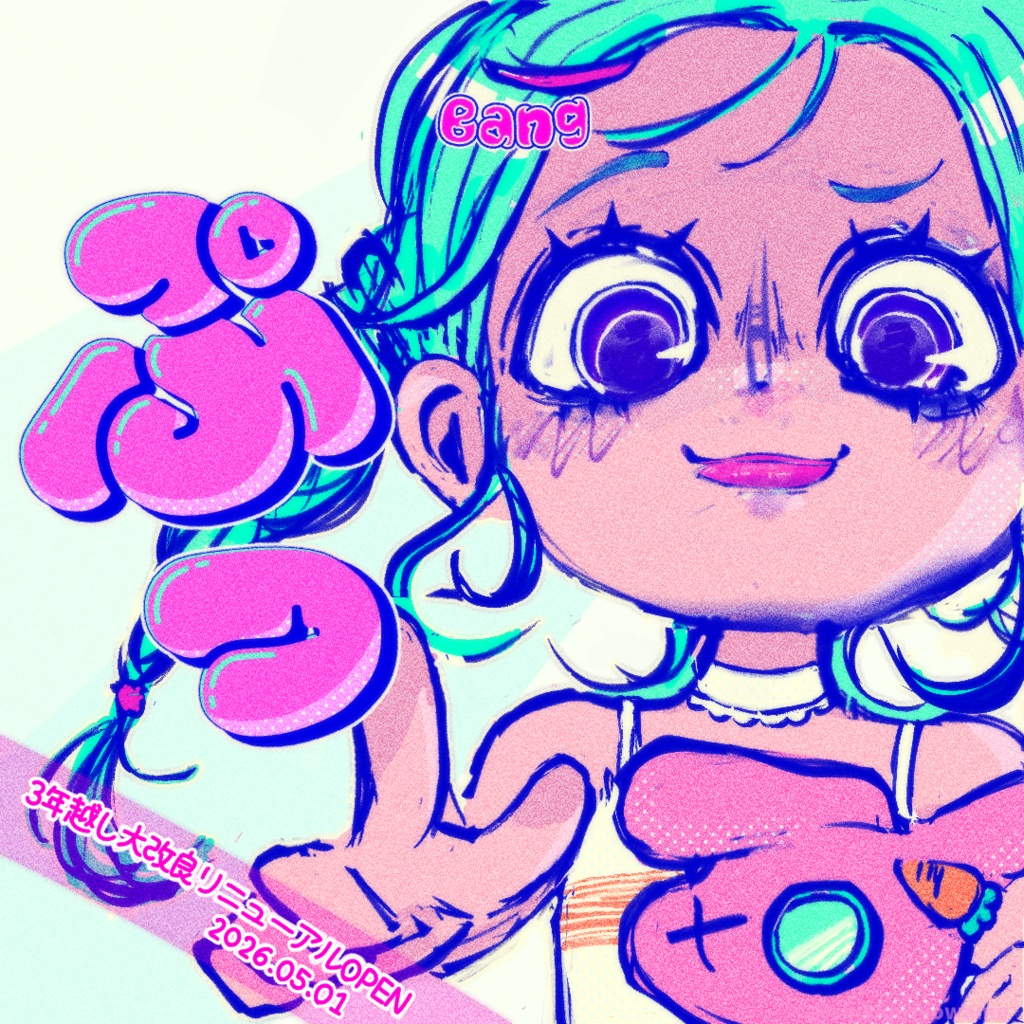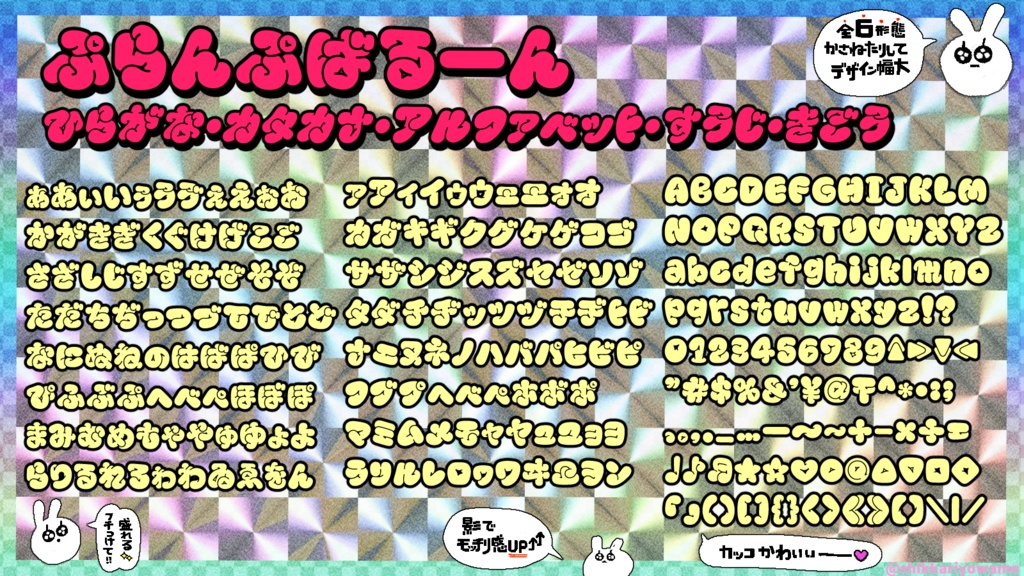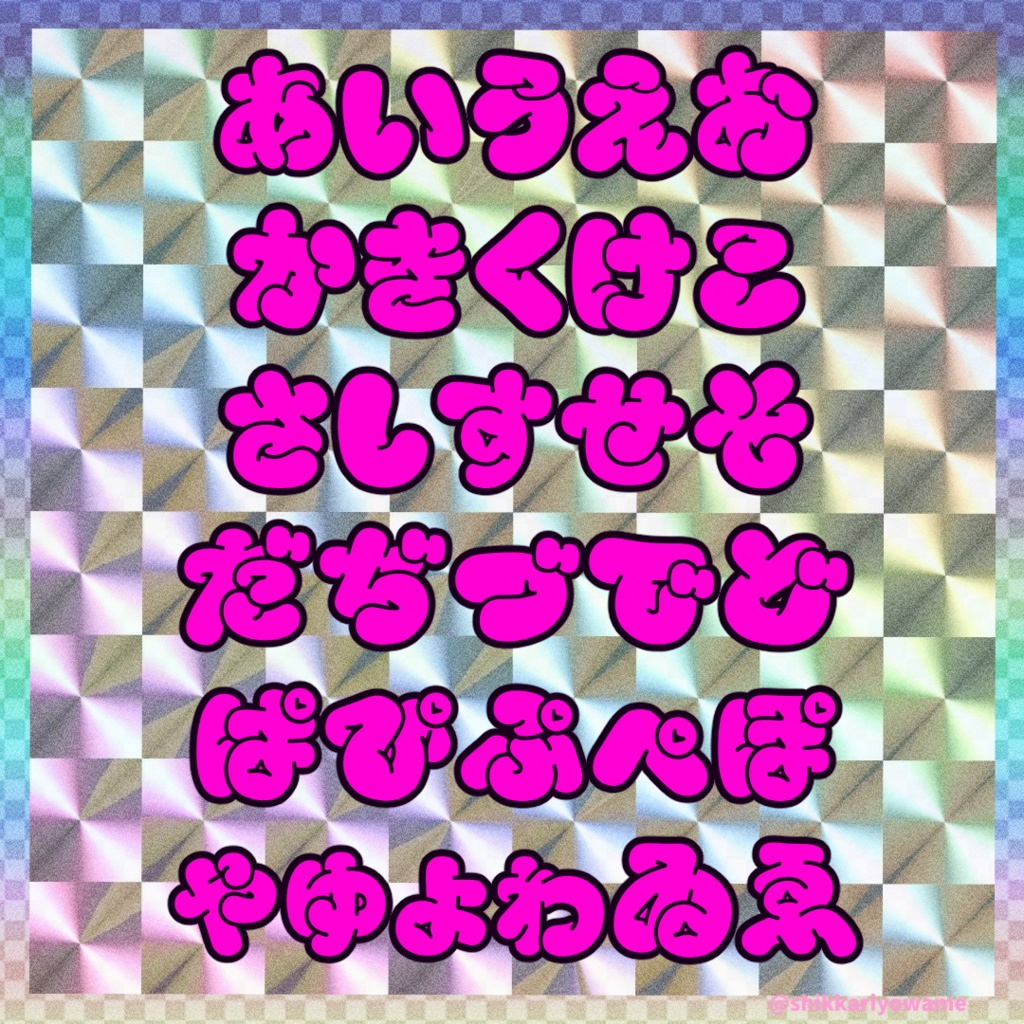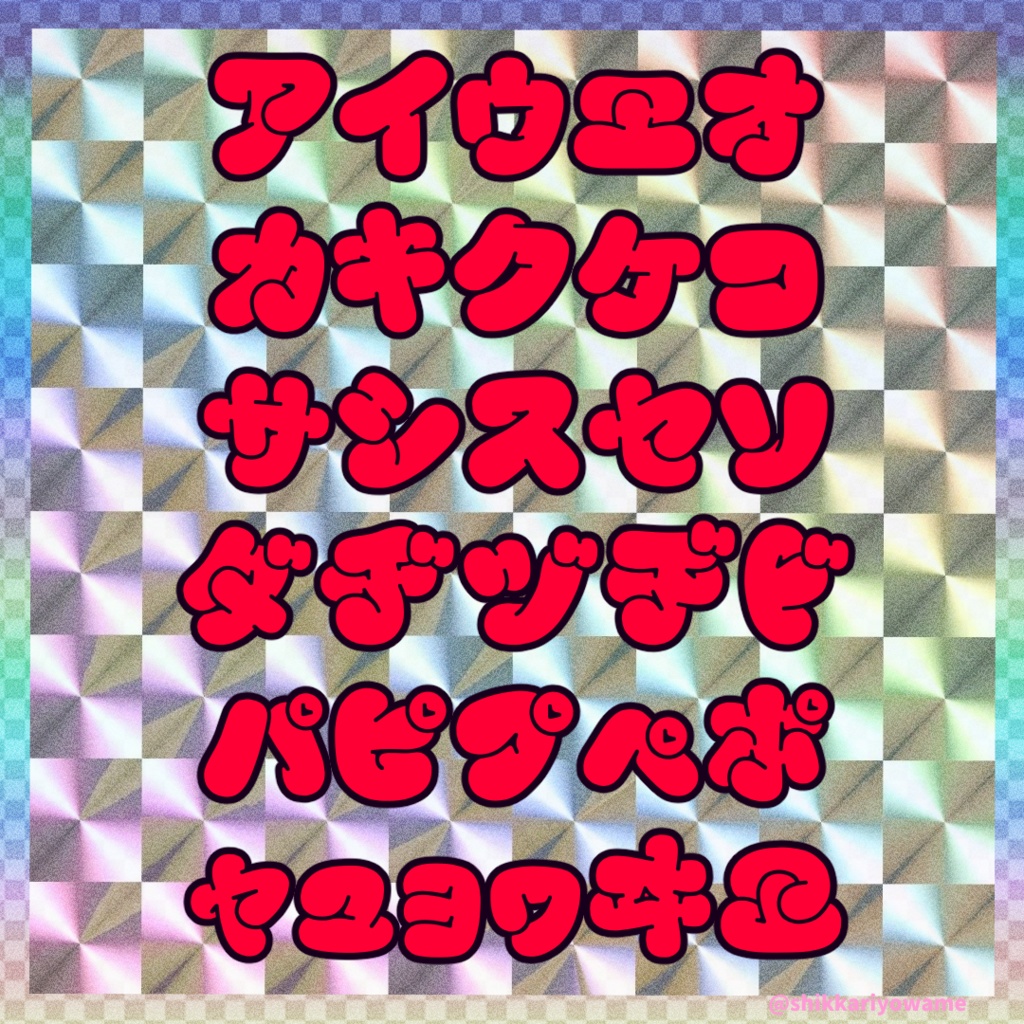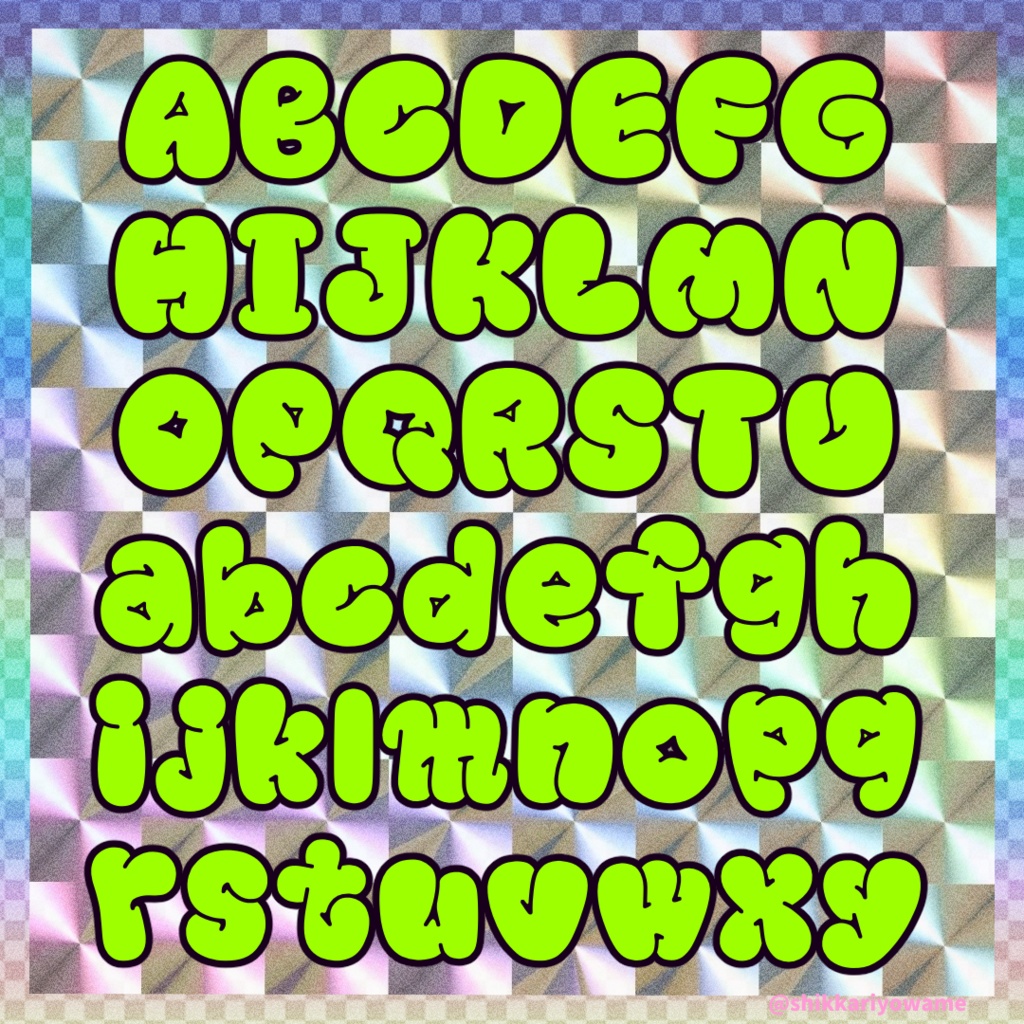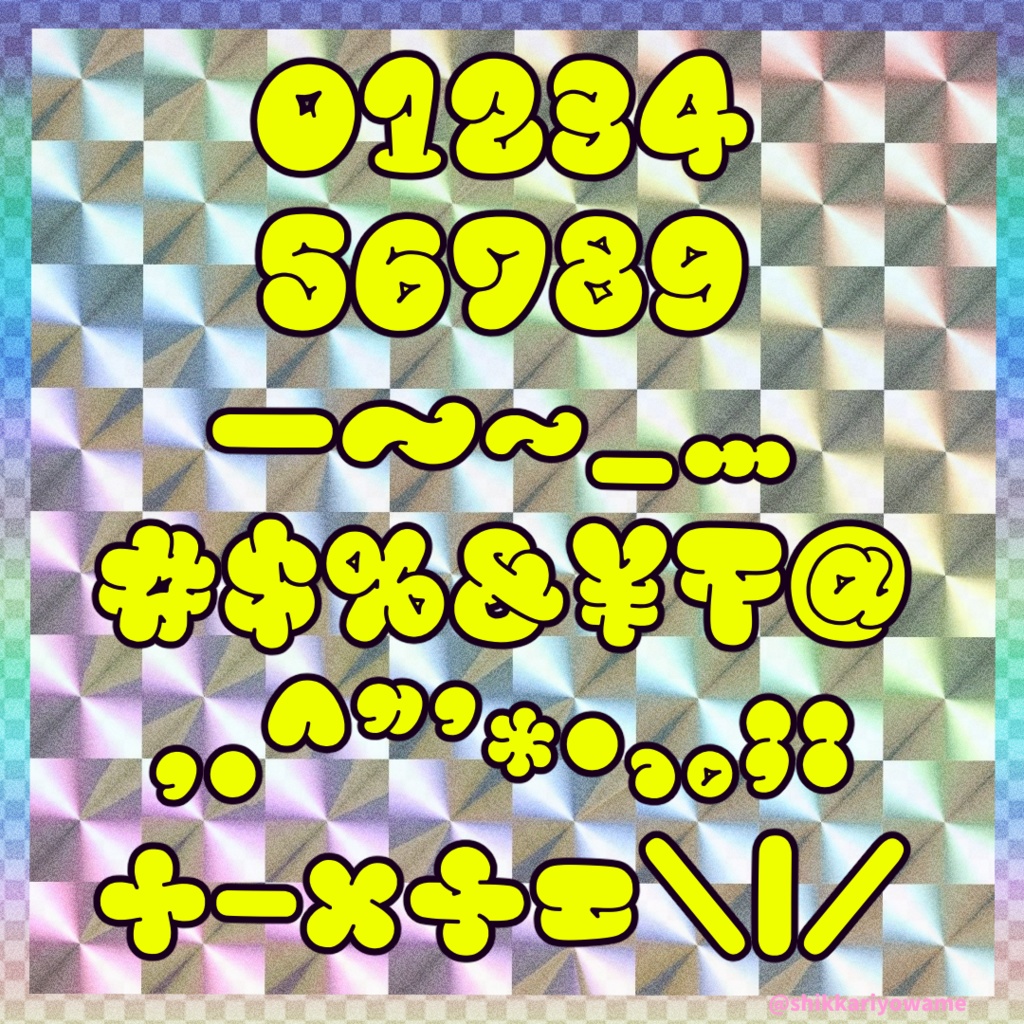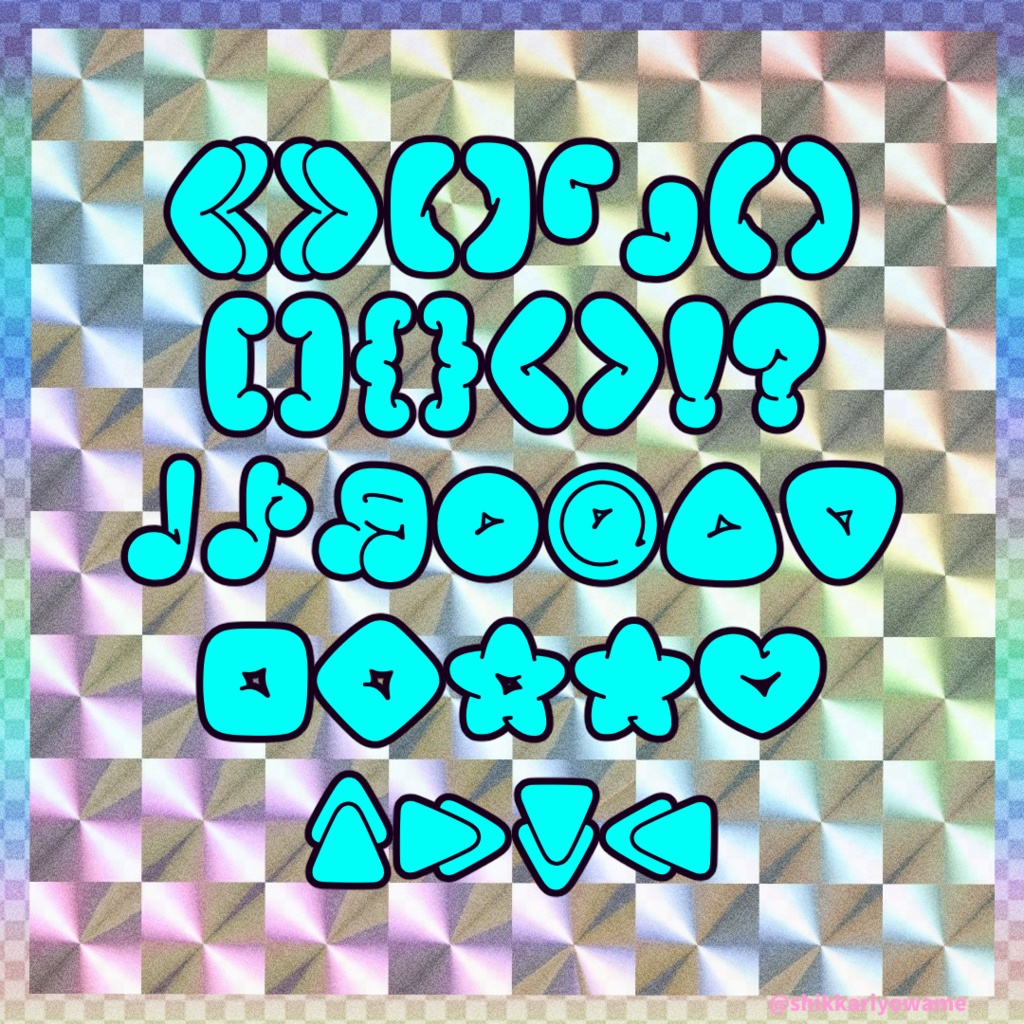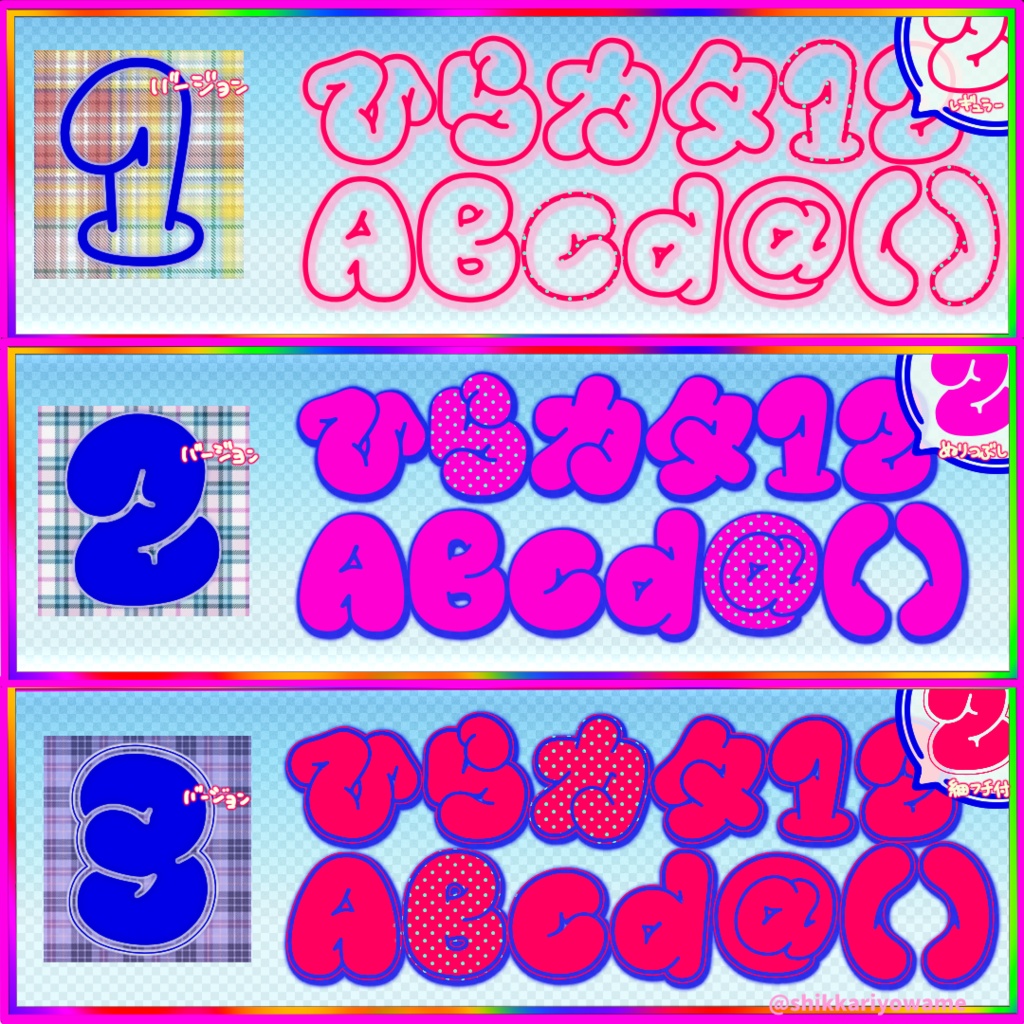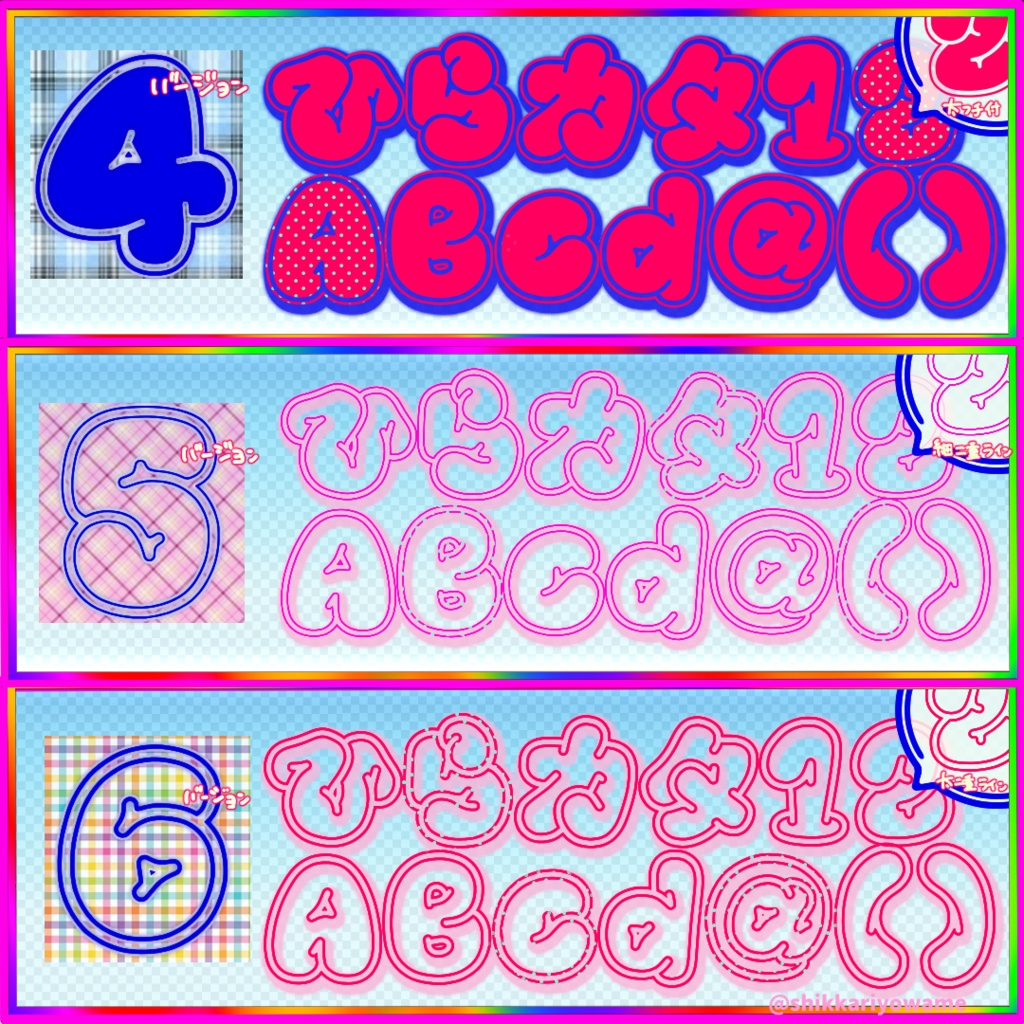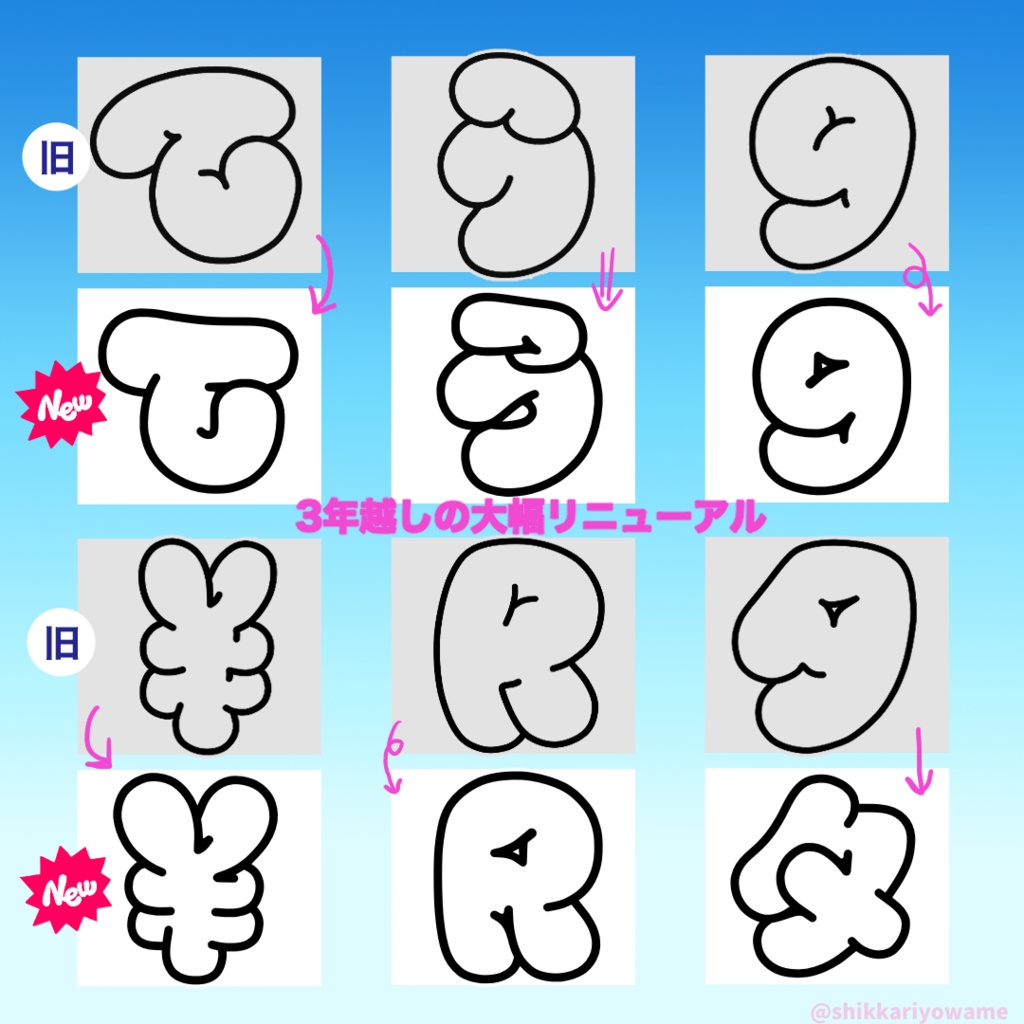
ぷらんぷばるーん【商用可】フォント
“ぷらんぷばるーん”/PlumpBalloon  \2026年5月より大幅改良し、リニューアルオープンしました/ 以前購入していただいたお客様、お待たせしました。お手数おかけしますが購入履歴からダウンロードお願いいたします。 【概要】  破裂するぐらい膨れ上がった風船のぷっくり感をイメージして作った手書きフォントです。 ぷらんぷばるーんは1/2/3/4/5/6 縁、塗りつぶし、縁付き、二重ライン、細目太目と全6種類のバージョン違いを用意しており、自由度が効きバリエーションが豊かなのでより一層デザインの幅が広がります。 コラージュやロゴ等一気に華やかにし、デザインに重宝!!   【収録内容】 ・ぷらんぷばるーん1/2/3/4/5/6(6つのバージョン違い同梱) ・利用規約 ・OTFフォント ・ひらがな、カタカナ、数字、記号、アルファベット 【無料版について】  ぷらんぷばるーん1/2(ひらがなのみ)の2形態を無料でお使いいただけるフリーフォントご用意しております。 Xアカウント( https://x.com/shikkariyowame2 )をフォローでどなたでもお使いいただけます。 無料版の商品ページをつくりしましたのでそちらからDL可能です。 → https://b1b1.booth.pm/items/8289382 【利用規約】 商用利用可能です。 (ご依頼での使用、ロゴ、映像、電子書籍、ゲーム、成人向け作品での使用、変形・加工も可能) 著作権は放棄しておりません。 フォントファイルの無断再配布、販売、譲渡、商標登録は禁止です。 (商標登録は加工した画像は可)  当フォントの使用に関連して生じたいかなる損害、トラブルは作者は責任を負いません。自身の責任でご使用ください。 詳細はフォントファイルと一緒に規約テキストを同梱しておりますので、そちらからご確認お願いします。 (※ https://lit.link/shikkariyowame からもご確認いただけます) ※フォント更新 2026/05/01 すべて改良+6形態 05/09 フォント表記名バグ修正